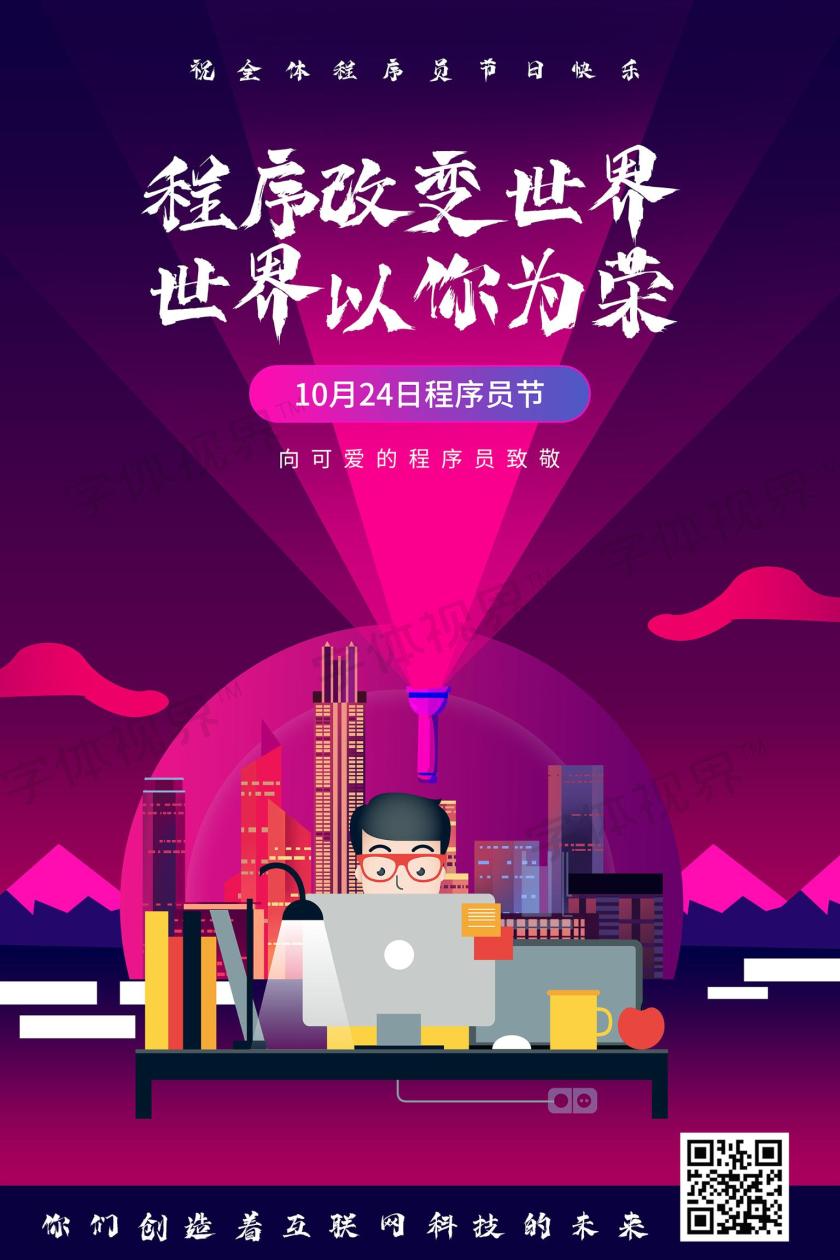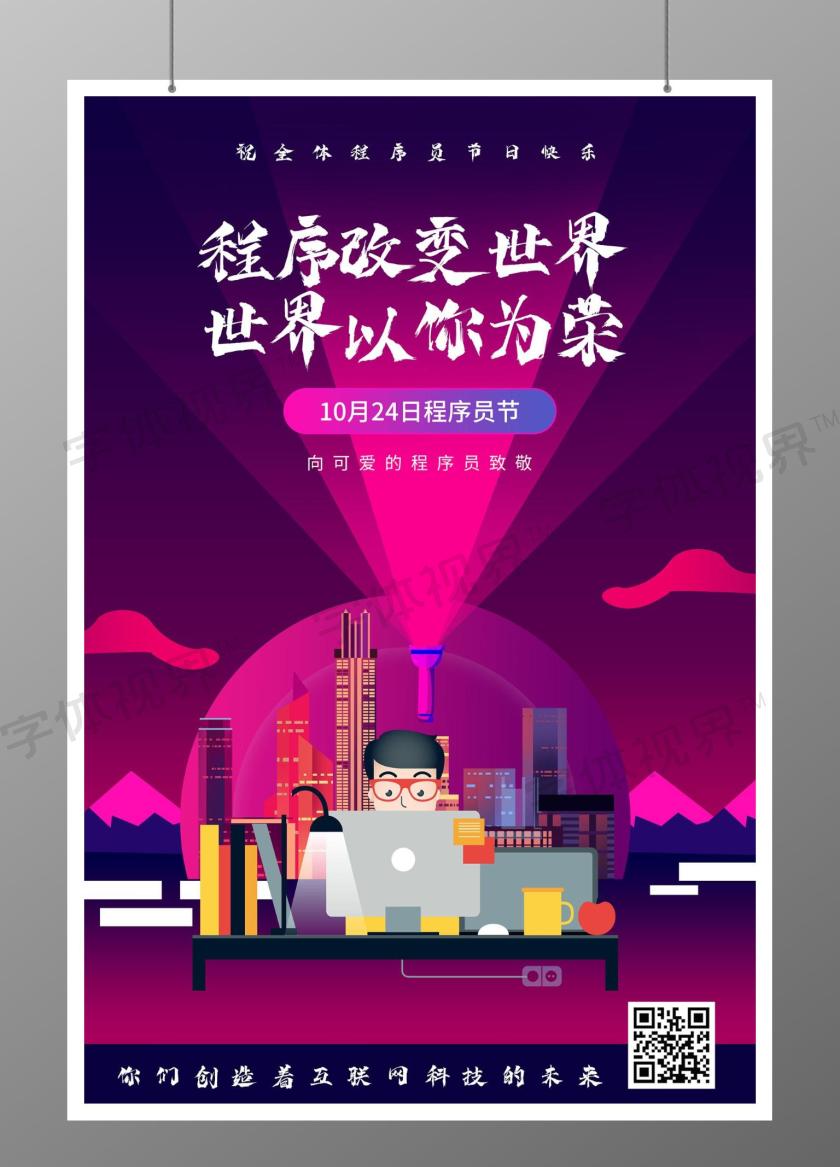
大气简约紫色程序改变世界以你为荣宣传海报程序员
这是一张关于程序员宣传海报设计图片,大气风格设计,以紫色为主色调,设计成程序员宣传海报模板,主体文字图片皆可替换修改,也可用于程序员宣传海报、世界海报、程序员海报、节宣传海报、宣传海报、程序员节海报模板素材,简约大气紫色系程序改变世界世界以你为荣程序员节宣传海报格式为PSD,作品编号:512906,尺寸为3543*5315像素,欢迎会员免费下载。